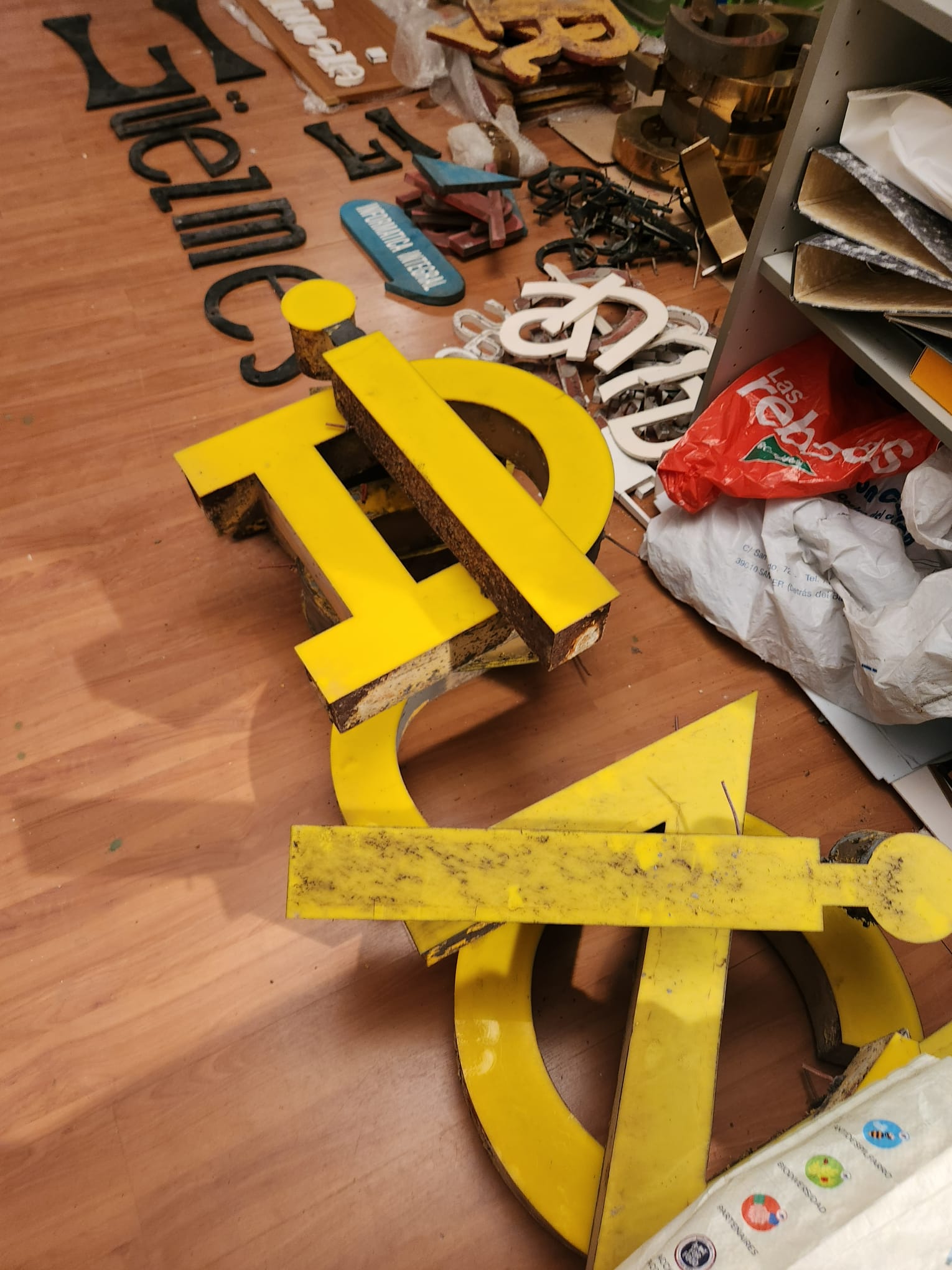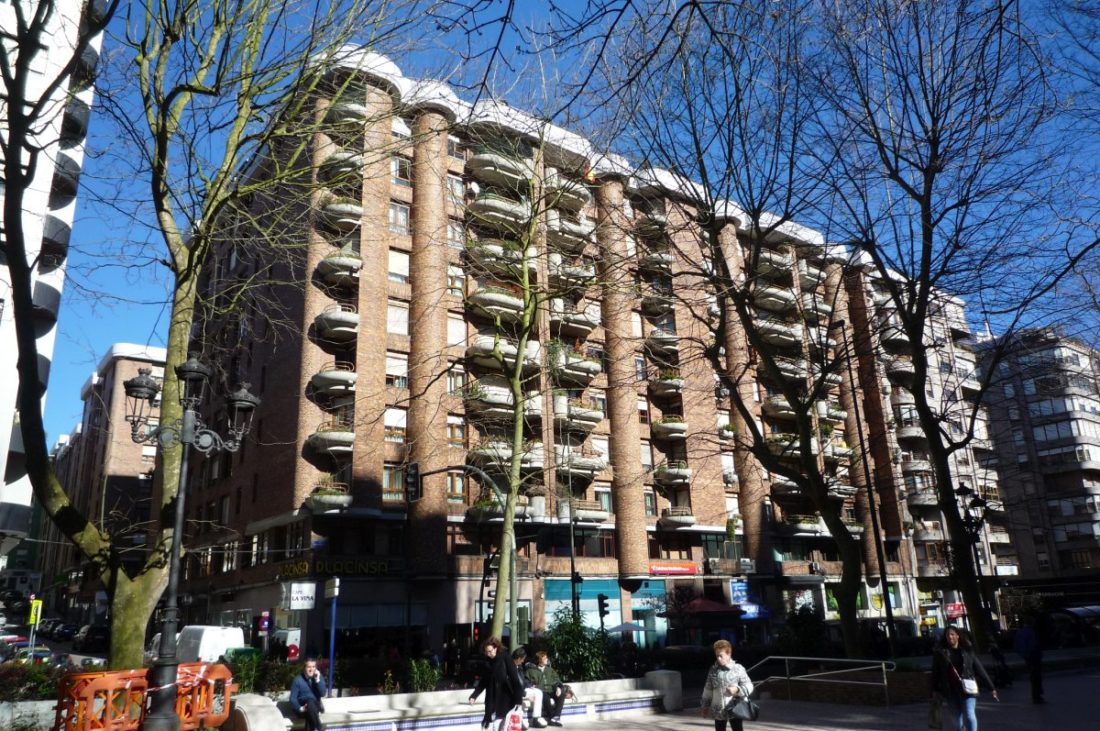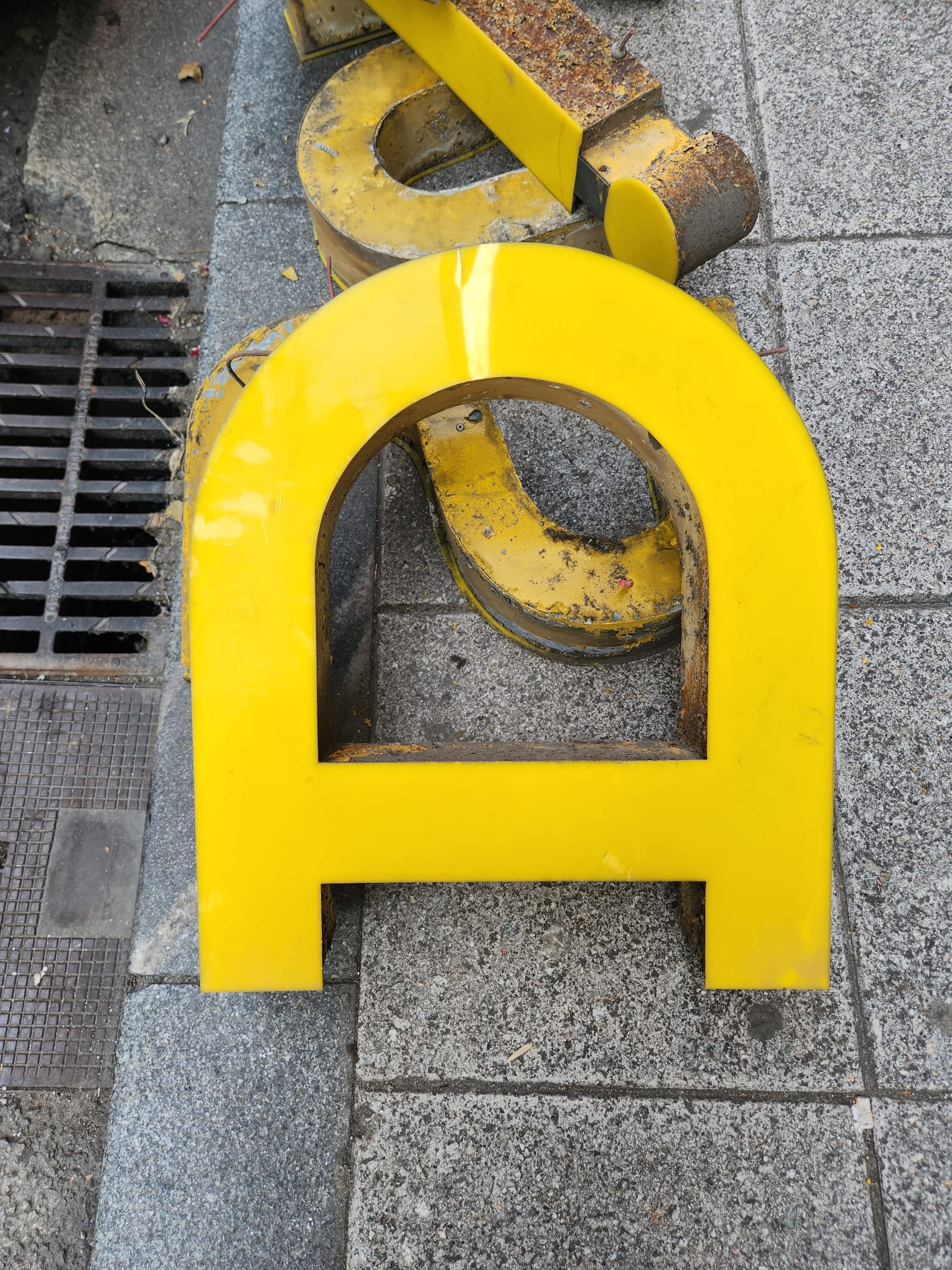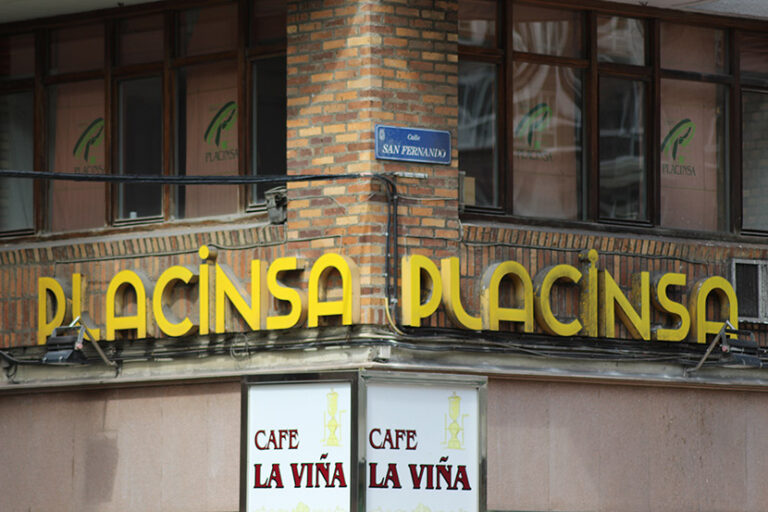
Recientemente hemos recogido las letras de los rótulos de PLACINSA, la empresa constructora. Los rótulos estaban instalados en la esquina, con esa maravillosa tipografía, integrándose en propio edificio de viviendas, construido en 1976 por la propia empresa bajo el diseño del Arquitecto Fernando Obregón Ansorena y que forma parte de ese catálogo de patrimonio arquitectónico.
Se han podido salvar gracias al aviso de Eduardo Bra de Trámites Fáciles Santander , que se han instalado en las antiguas oficinas de  la constructora y  han desmontado los rótulos. Ahora forman parte del Archivo del Patrimonio Gráfico de Cantabria.